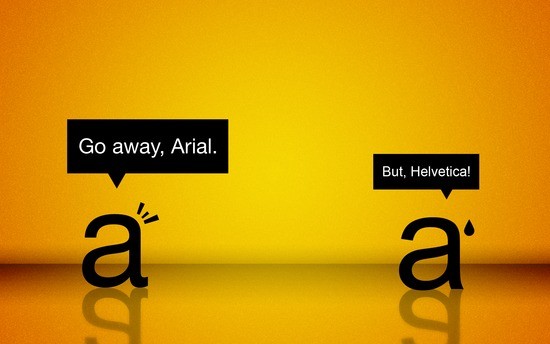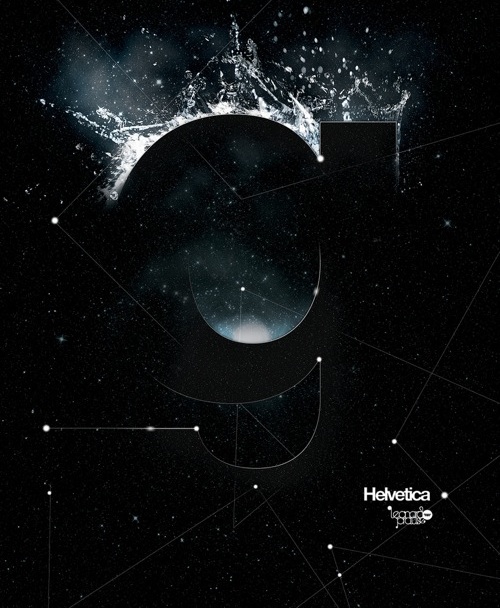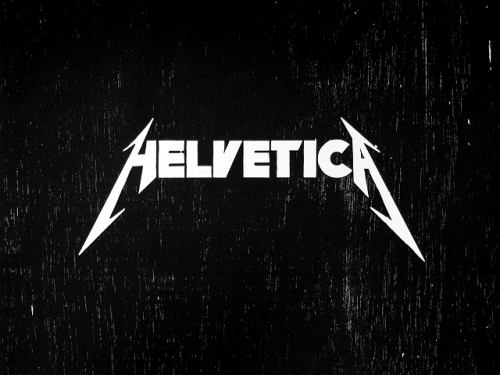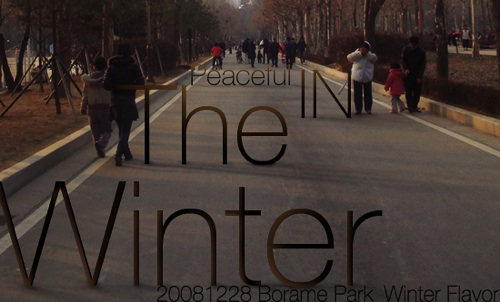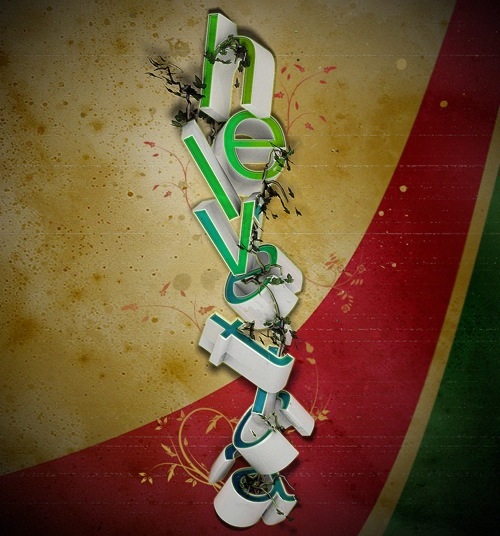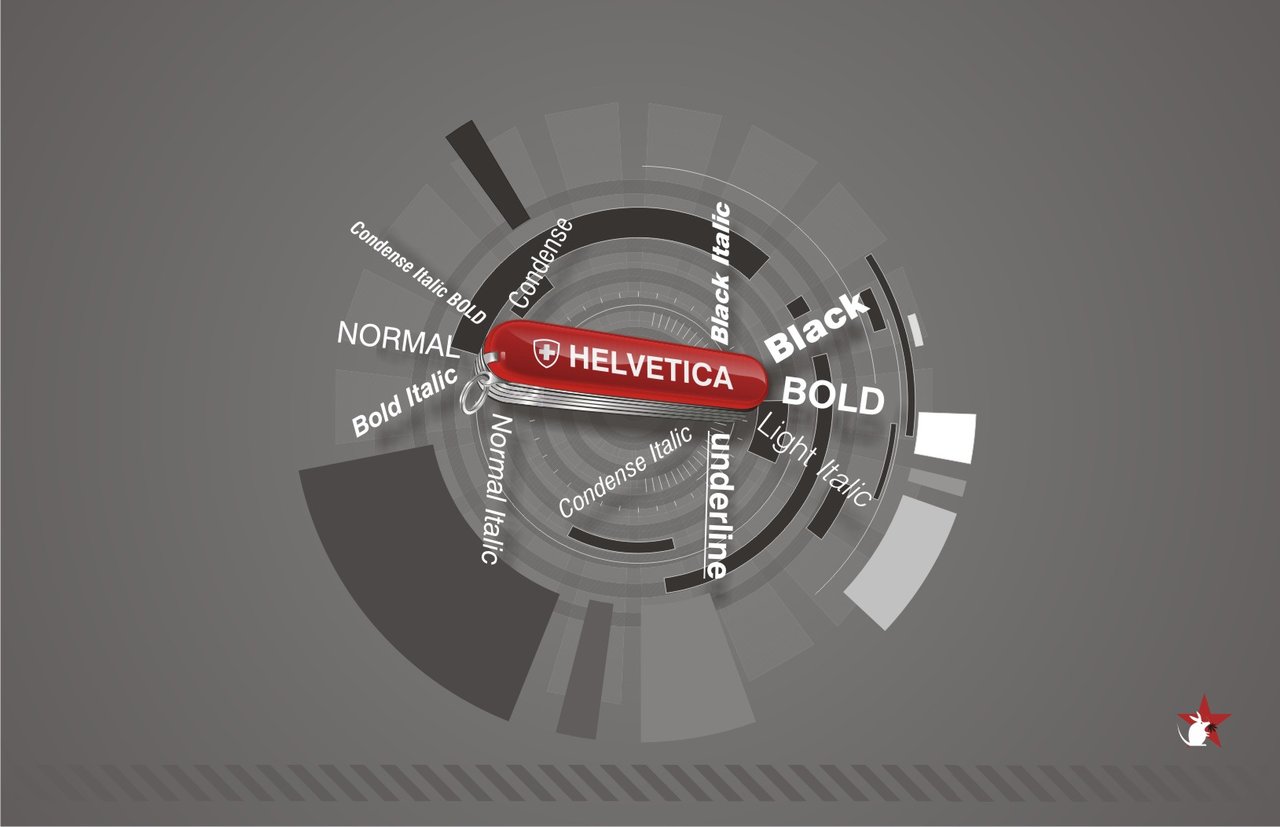
Hay que ser diseñador para amar esta colección de posters y entender la trascendencia de ellos.
Se dice que no volverá a existir una tipografía como Helvetica, tan universal, tan perfecta, tan sin pretensiones. Ser diseñador, independientemente de que nos guste o no, es reconocer su caracter y elegancia, capaz de embonar en casi cualquier diseño.
Desizn Tech compila 45 ejemplos increíbles donde se usa esta tipografía como fondo y forma; una colección de lujo que cualquiera de nosotros desearía tener en sus paredes; la visita al sitio es inevitable.
El póster de la navaja suiza me parece exquisito, quizás porque además es el que tiene una de las retóricas más marcadas. Otros son puramente estéticos, muy lindos, pero sin retórica (y particularmente los prefiero con). El de Metálica quizás habría estado mejor usar la Helvética con la H y la A de las puntas con esas “flechas”. El que está con Arial es muy bueno y llama a una vieja polémica: el de las tipografías imitadas (Azkidenz-Helvética-Folio-Arial; Palatino-Book Antigua-Aldus; Bodoni-Didot, Futura-Century, etc, etc). Sería bueno tratarlo como tema aparte. Saludos!
En el primer póster se nota la gran diferencia entre las 2 fuentes…
Definitivamente, la prueba de oro para todo diseñador es cuando se deja de confundir Arial con Helvetica… Helvetica es simplemente perfecta, mientras que Arial es sólo una fuente neutra.